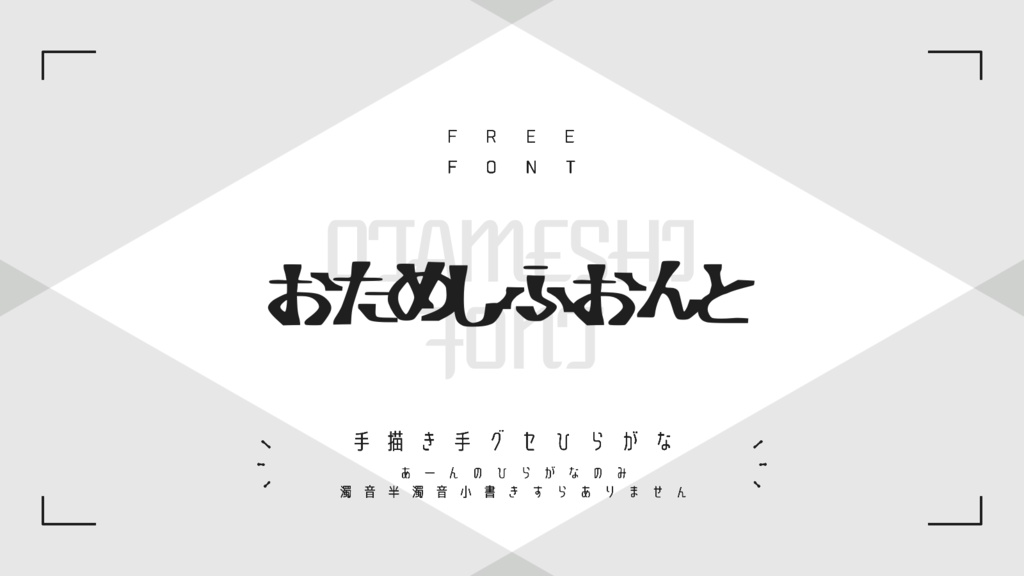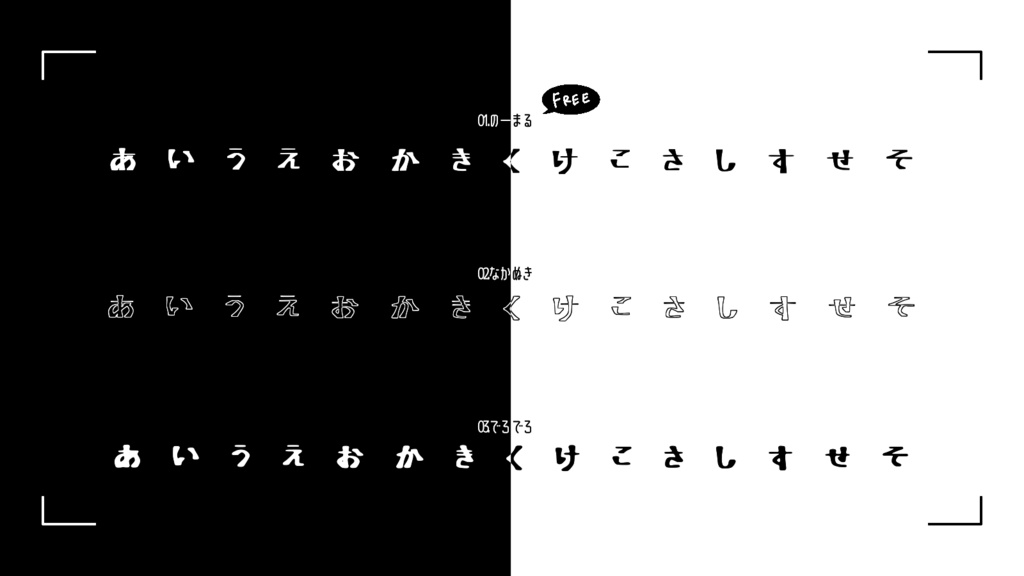
前回のを作る前にテストとして作ったフォントです ( https://ko-no-za-ma.booth.pm/items/4450887 ) ベースラインの調整すらしてないので、 縦横に並べたときにバランスが悪いものがあります ご理解の上、飾りなどにご使用ください 収録文字は「あ-ん」のひらがな48字のみです 濁音半濁音や小書きなどもありません ───────────────